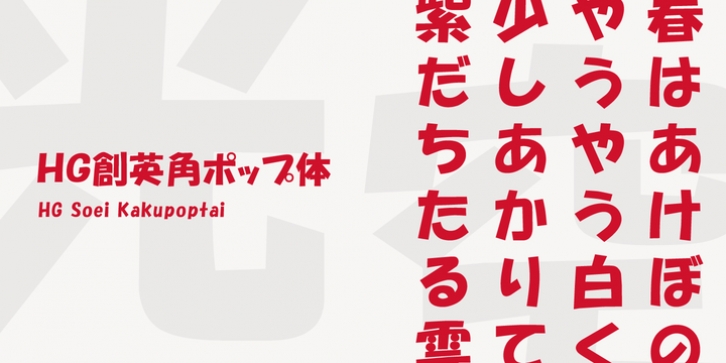
HG創英角ポップ体は、水本恵子氏がデザインした「創英ポップ体1」を字母とする書体です。店頭広告用文字のスタイルを模して作られた書体で、楽しく、軽快な書体です。極太角ゴシックのイメージをベースに作られていますが、それをやや崩し、柔らかさも取り入れ、フリーハンドで書いたイメージを残しています。見やすくするため、ふところは可能な限り大きくなっています。店頭のPOP、チラシ、看板などに最適の書体です。